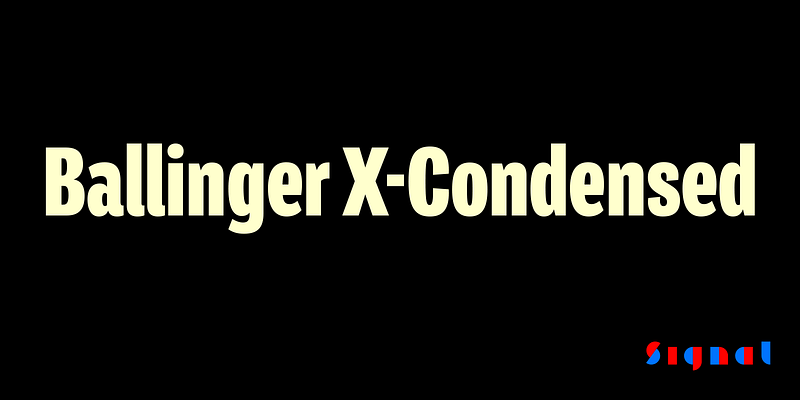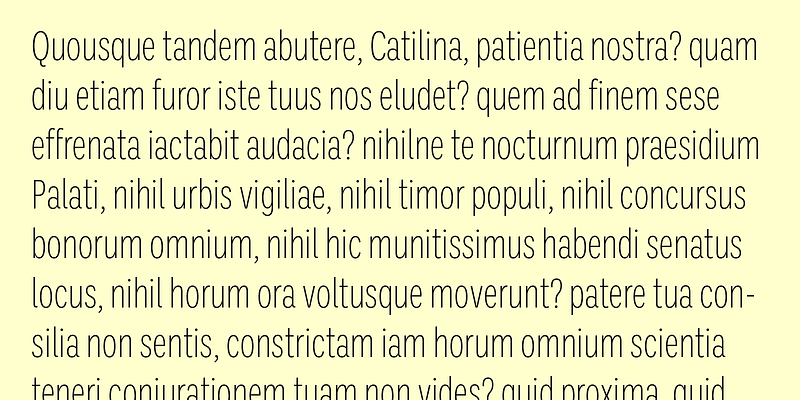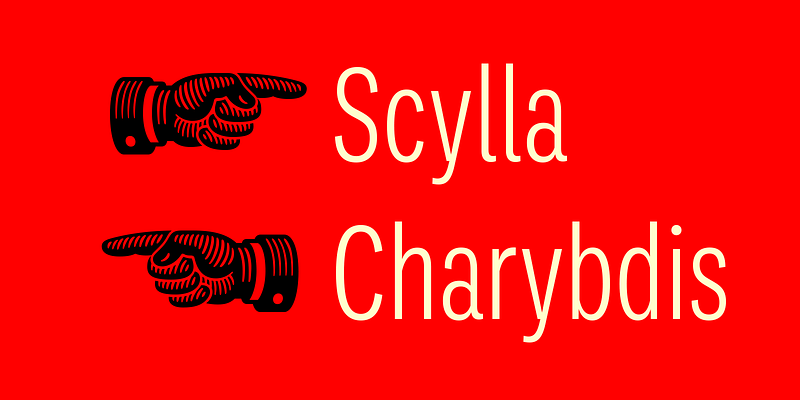
このフォントの原型となる DNA は、ゆったりとしたカウンターと x-ハイト、簡明な形、そして陽気なほどの効率性の良さが感じられる点に見ることができます。しかし、大幅に洗練されたエクストラコンデンスのスタイルは、映画のクレジットや法的免責事項、副作用のリストには理想的です。特徴として、セミオールドスタイルの数字、大文字と小文字を区別する約物と区切りが含まれます。また、全角、コンデンス、等幅のバージョンもあります。